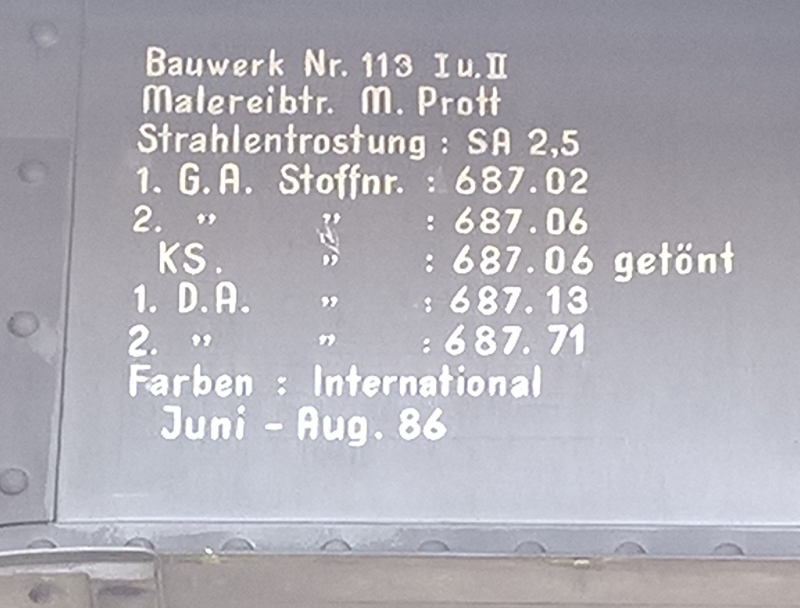
Beim Spazierengehen im alten Viertel entdeckt und ein, zwei Momente gerätselt, was an diesem Viadukt (U-Bahn-Brücke Eppendorfer Baum) getröstet werden soll...
Solche Angaben des Beschichtungsaufbaus kenne ich von Hamburger Stahlbrücken schon seit der Zeit, als noch der G. A. (Grundanstrich) noch in Bleimenninge, sowie der 1. und 2. D.A. (Deckanstich) in Eisenglimmerfarbe ausgeführt wurden.
Nämlich, dass immer, wenn 2 Schrichten der gleichen Farbe aufeinander folgten, eine der Schichten so abgetönt wurden, dass man bei der 2. Schicht auch erkennen kann, dass diese wiklich deckend über der ersten Schicht liegt.
Würde man 2 mal mit exakt der gleichen Farbe lackieren, könnte man nicht sehen, wenn man dann in der 2. Schicht Stellen vergessen hätte.
Aber schön zu sehen, dass es noch 1986 Maler gab, die noch ohne technische Hilfsmittel eine Anschrift sauber mit dem Pinsel schreiben konnten